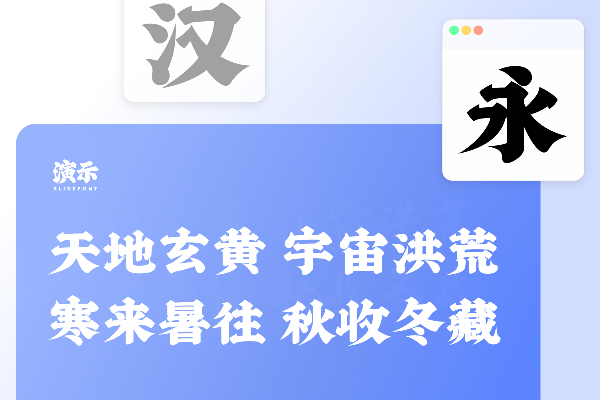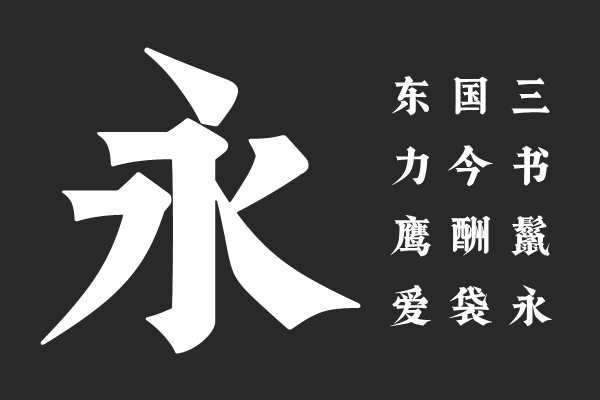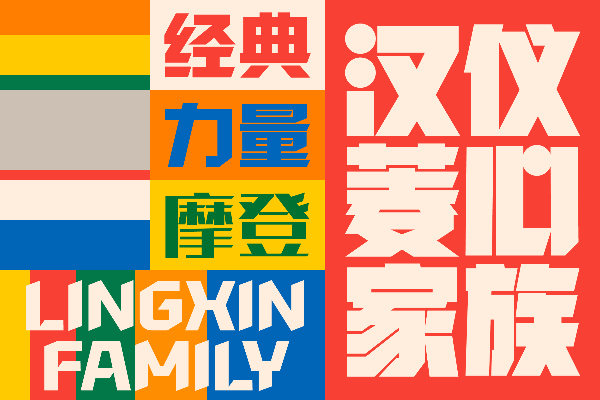
适合广告的字体推荐:8款提升设计高级感的字体
错误的字体会让高级的广告变得廉价,而合适的字体则能让你的品牌调性瞬间立住。
本文分享 12 款适合广告的字体,这些字体既有质感,又能在不同商业场景中精准传达情绪。选对它们,你的设计作品不仅更有说服力,还能显著提升客户的满意度,让你的创意在海报、屏显或社交媒体广告中脱颖而出。
站酷快乐体
站酷快乐体笔画圆润、活泼可爱,适合年轻化品牌、食品广告、促销海报。它自带的亲和力能拉近与消费者的距离。
演示汉楷宋
演示古风宋
演示古风宋是一款具有浓郁古典韵味的宋体字体。这款字体在传统宋体的基础上强化了古籍刻本的视觉特征,笔画保留了雕版印刷的粗犷质感,横细竖粗的对比更加明显,起笔收笔处带有手工刻字的细节变化。
适合古籍复刻、传统文化海报、国风品牌设计、文史类书籍装帧等需要营造古典氛围和历史厚重感的应用场景。
汉仪菱心体
汉仪菱心体几何切角处理,平衡了圆润与锋利,显得非常有动感。适合电竞产品、游戏宣传图。它是那种看一眼就让人觉得“很酷”的字体。
郑庆科静雅体
郑庆科静雅体是由字体设计师郑庆科创作的一款手写风格字体。这款字体笔画流畅自然,保留了手写书法的灵动感和温度,同时在字形结构上经过精心调整,保证了良好的可读性和规整度。笔触柔和细腻,转折圆润,整体呈现出恬静优雅的气质,既有手写字的亲切感,又不失专业排版的美观性。
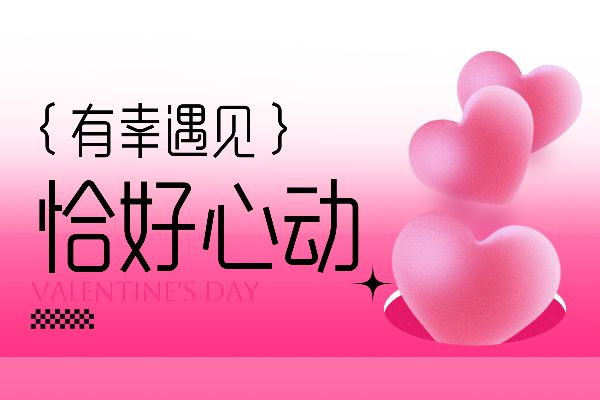
郑庆科帅黑体
郑庆科帅黑体是由字体设计师郑庆科创作的一款具有力量感和现代气息的黑体字型。这款字体笔画粗壮有力,结构紧凑扎实,横竖笔画对比明显,转折干脆利落,整体呈现出硬朗挺拔、刚劲有型的视觉效果。
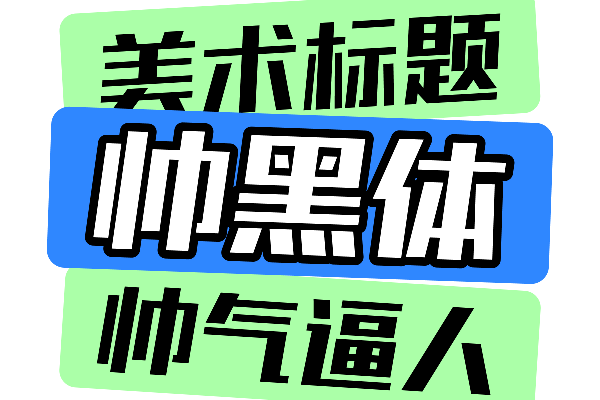
汉仪尚巍手书
汉仪尚巍手书不拘一格,带有粗粝的笔触感,非常有艺术表现力。适用独立咖啡馆、文创产品、潮流服装。它能让你的设计瞬间带有艺术家的独特视角。
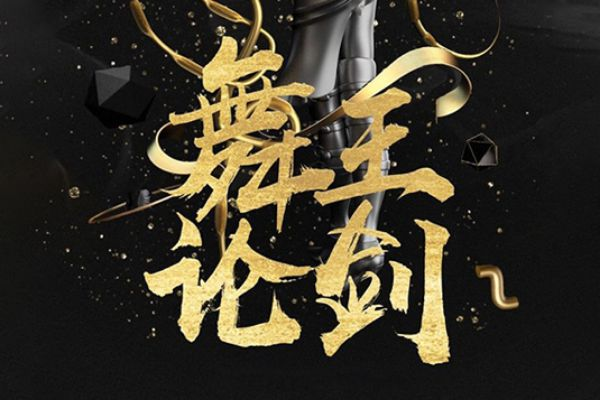
鸿雷拙书
鸿雷拙书是一款带有浓厚拙朴趣味的手写书法字体。这款字体刻意保留了书写的随性与不完美,笔画粗细变化自然,结构略显稚拙,带有原始的书写力量感。字形不求工整,反而追求一种质朴天真的韵味,笔触率真直接,转折处显露出书写的速度感和力度变化。
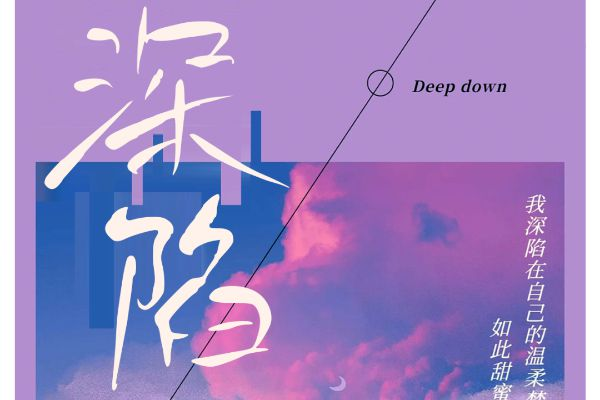
如何挑选适合你的广告字体?
作为过来人,我给你的建议是:先想情绪,再想字体。
在挑选字体前,问自己三个问题:
- 我的产品想传达什么感觉?(是狂热、宁静、还是严谨?)
- 目标客户是谁?(是年轻人、精英阶层、还是普通家庭?)
- 字体要在哪里呈现?(是户外大牌,还是手机屏幕?)
好的字体不是为了喧宾夺主,而是为了精准地辅助你的视觉表达。您可以多在字由上试用这些字体,其实设计就是在做减法,去掉多余的装饰,选对一款好字体,你的广告作品离“爆款”就只差这一步了。希望这些推荐能给你的创作带来灵感,让每一件作品都成为你职业生涯的里程碑。